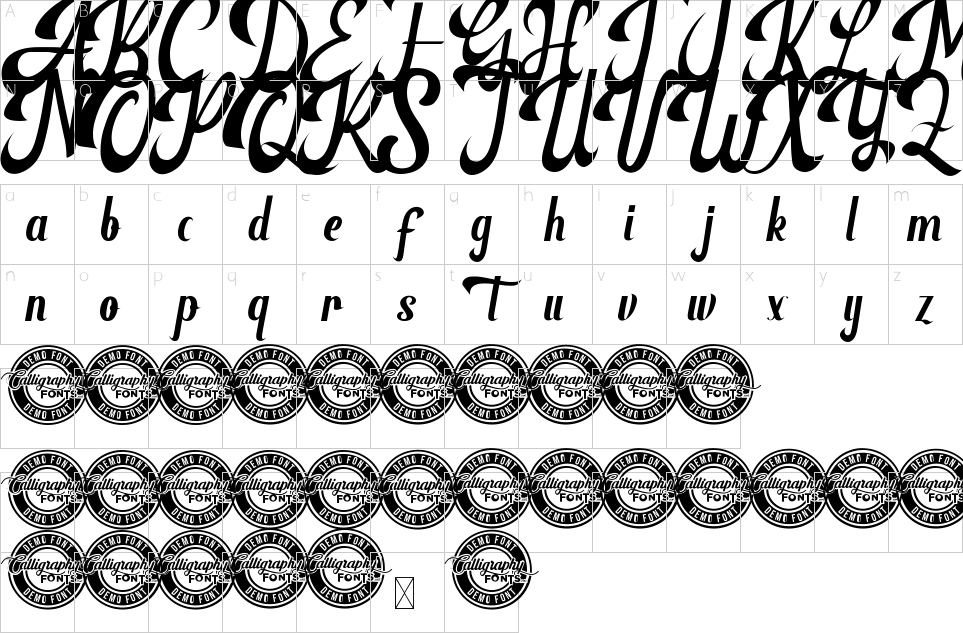
Descubra a beleza do Grantsburg Font, uma elegante opção para designers que buscam graça e clareza na sua tipografia. Essa fonte foi cuidadosamente criada por CalligraphyFonts e já foi baixada 4,275 vezes. Seja para projetos de design web ou impressão, Grantsburg oferece um visual atraente que se adapta perfeitamente às suas necessidades gráficas. O Grantburg font é uma escolha ideal para quem busca qualidade sem comprometer a diversidade e elegância das letras. Descubra agora mesmo como essa font pode enriquecer seu trabalho de design.